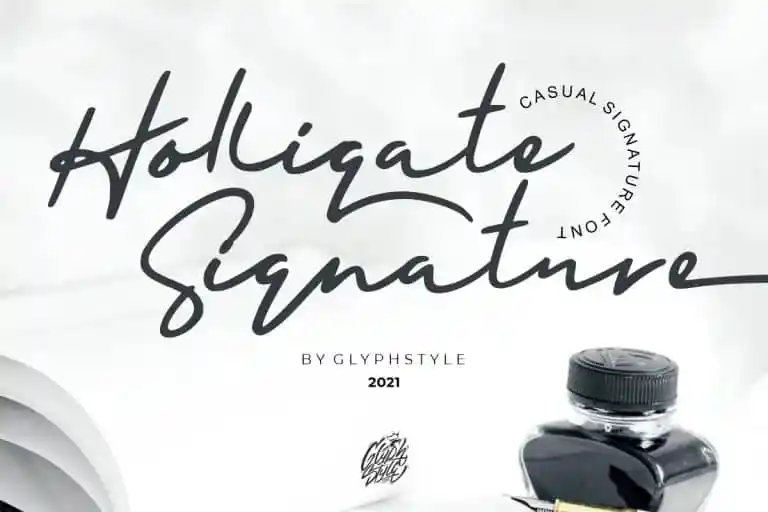
Holligate Signature Script Font – Download Grátis
Introduzimos a Holligate Signature Script Font, uma elegante fonte escrita à mão com estilo de assinatura. Esta bonita fonte de script oferece seu toque pessoal ao próximo projeto de arte que está criando. Ideal para casamentos, marcações, identidade visual, como entrevistas, cards de visita, logotipos de produtos e muito mais. Com um olhar elegante, sofisticado e moderno, a Holligate Signature Script Font é perfeita para tornar suas criações únicas e memoráveis. Sinta-se à vontade para experimentá-la em vários projetos e veja como ela adiciona aquela pitada especial que seu trabalho merece.